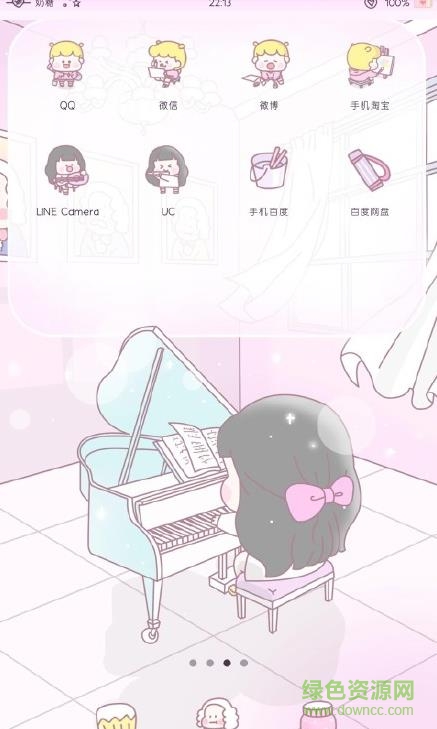
慧心的情愫體字體ttf十分不錯,其內(nèi)的字體樣式就像仙女一樣很暖哦,可以應(yīng)用到手機上帶給你最佳的使用體驗,同時更能讓你感受到濃厚的典雅氛圍,快來綠色資源網(wǎng)下載吧!
很不錯的字體哦,微博上好多小伙伴都在使用了,能夠在手機上帶給你最佳的顯示效果,還能夠發(fā)給好友讓她羨慕不已呢!